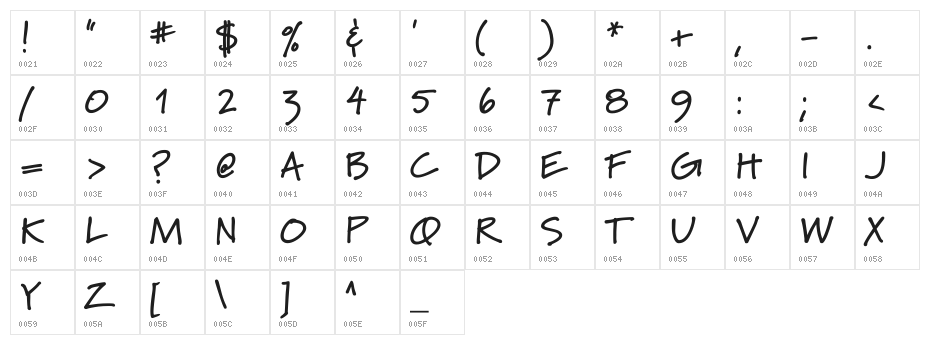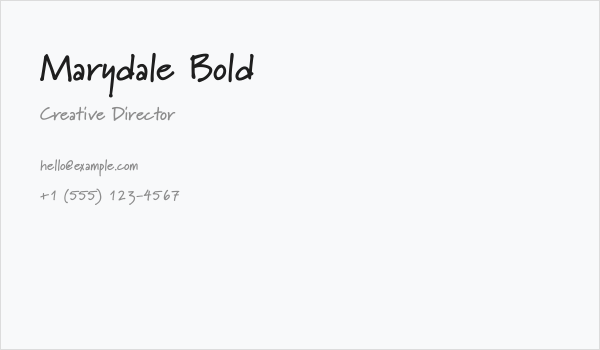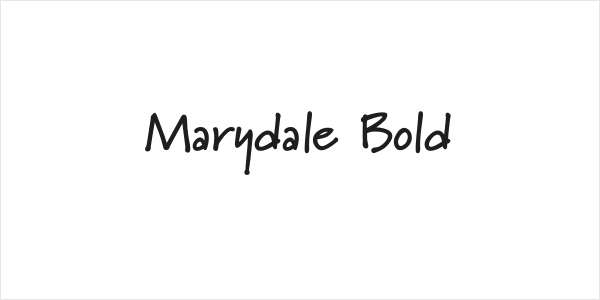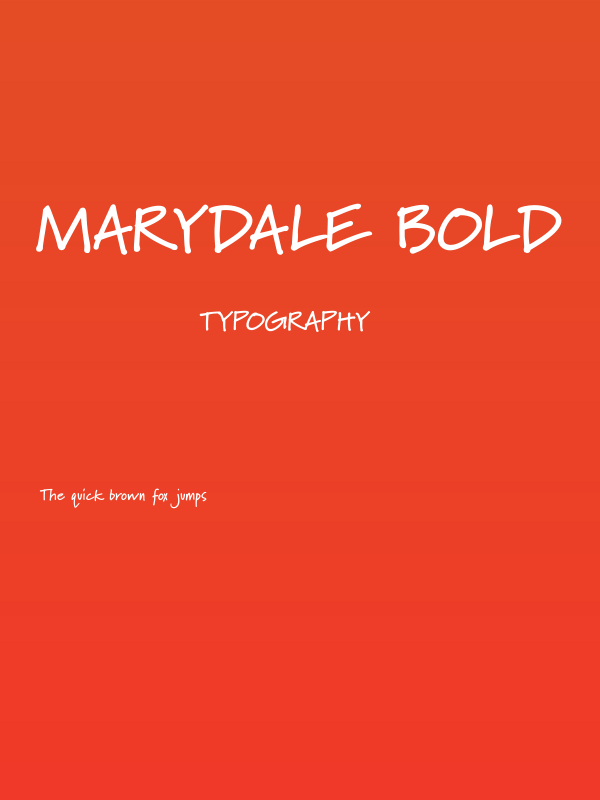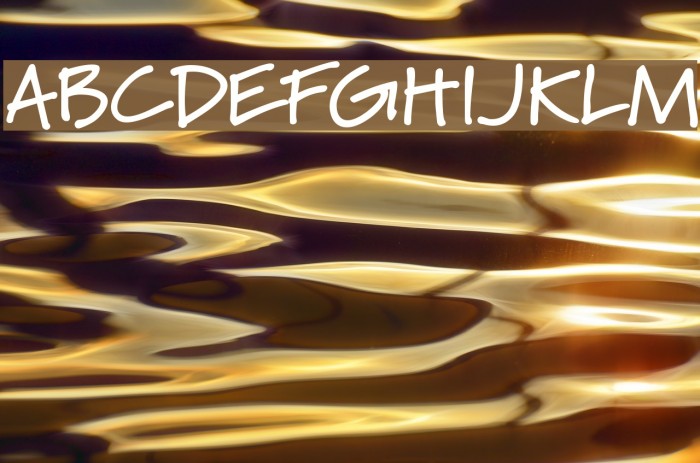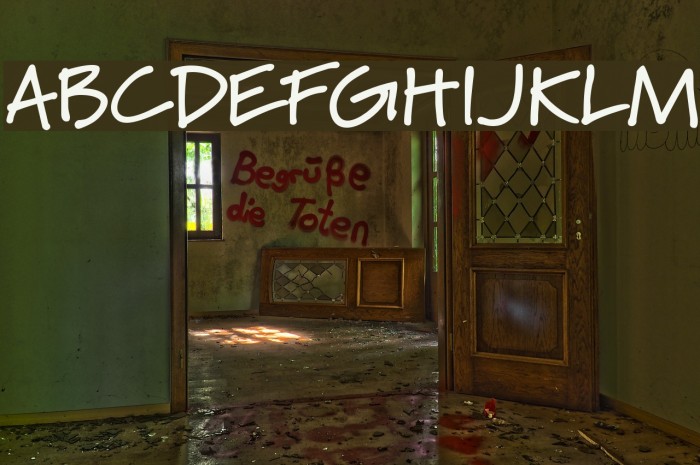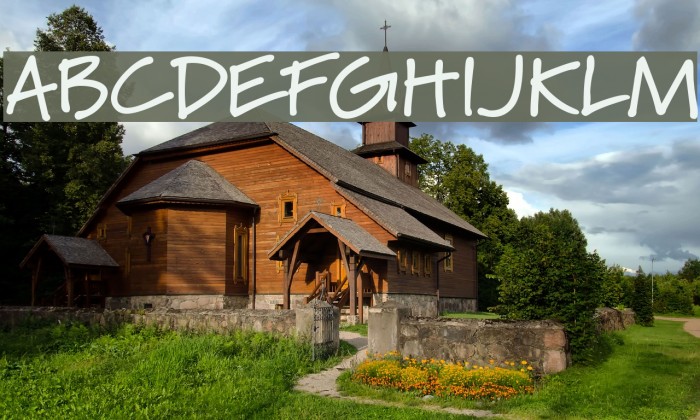
Marydale Bold Font
| Nom | Marydale Bold |
| Poids | Bold |
| Style général | Casual |
| Cas d'utilisation | Logos, Headlines, Informal Text |
| Projets proposés | Great for personal branding, social media graphics, greeting cards, and informal invitations. |